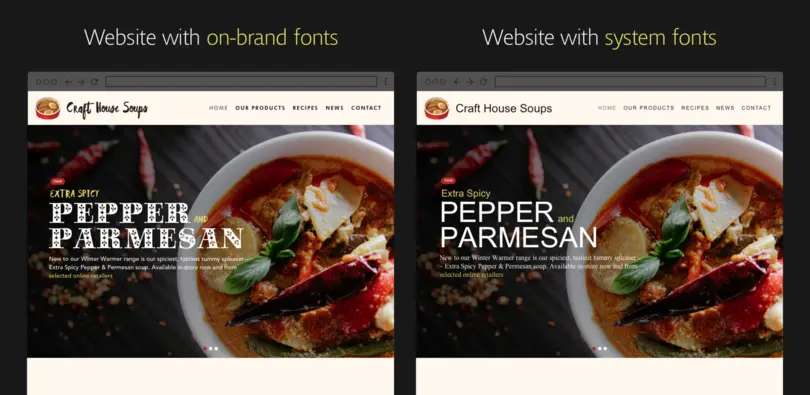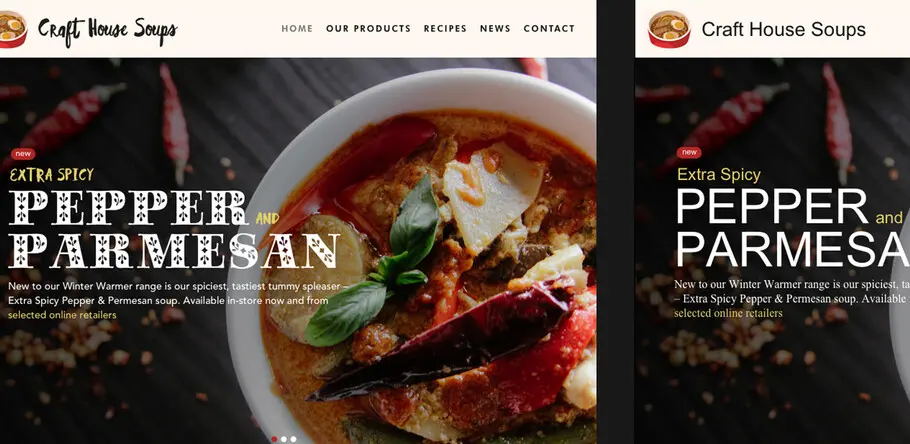
良い結果をもたらさないフォント:必ずしも期待通りの結果を得られない理由
「 Sharing your brand font with third parties—a design or marketing agency, a freelancer, or a vendor such as a printmaker—can be a tricky process. 」
Fonts behaving badly: Why you don’t always get the result you expect.
製品に合うフォントを選ぶ時、どれを選んでも問題なく思った通りの機能をすると思っていませんか?どこでどう使おうと、フォントはどこまで行ってもただのフォントであり、それ以上でもそれ以下でもない、と。 しかし実際はそうではありません。その場その場で考えなしにフォントを選んでしまうことによって、製品のビジュアルを大きく損ねてしまうことになりかねないのです。
フォントはさまざまな用途に合わせて作られた「ソフトウェア」と見ることが出来ます。例えば、システムフォントとも呼ばれるデスクトップフォントはコンピューターに既にインストールされた状態で届きますし、そういったフォントは印刷のプロジェクトで使用され、一部はウェブサイトでも使用されます。
その一方で、ウェブフォントは必要な時にサーバーとウェブサイトやデジタル広告からダウンロードされます。ウェブフォントは変化が早いデザインや、モバイルブラウジングに特に向いています。
フォントがブランドに与える影響
今後ブランドや会社にとって重要な事の内1つに、「ユーザーの全てのタッチポイントにおいて一貫性を実現させること」があります。
中でも、特に若いデジタルネイティブ世代は、無数に存在するプラットフォームのうち、自分の選んだもので円滑に製品やアプリなどを使用することが出来ることはもはや当たり前です。
Googleによると、オンライン上での利用を一つのデバイスである一つのアプリやウェブサイトを利用し始めたユーザーのうちなんと65%が、別のデバイスでも同じアプリやウェブサイトを使い続けています。
フォントを適材適所で活用できないと、ブランドとしての一貫性がなくなりかねません。これまで築き上げてきたブランドイメージが、ネット上では全く異なるものになってしまうこともあるのです。
そんなことが起きてしまえば社内はもちろん、ユーザーのブランドへの信頼も失いかねません。では、どのような時にこのような事態が引き起こされてしまうのか見てみましょう。
失敗事例1:デフォルトのシステムフォントの罠
システムフォントとは、OSに最初から組み込まれているフォントのことです。実はMac OS、Windows、どちらもバージョンの違いによって異なるシステムフォントを持っています。
例えばもし、お客様のOSに搭載されていないシステムフォントをウェブ上で使用してしまった場合、どうなるのでしょうか。
左側のウェブサイトはウェブフォントを使用して設計されており、あらゆるユースケースで一貫したブランド体験が保証されます。右側はシステムフォントで作成されており、デフォルトではランダムオプションが設定されています。
左のウェブサイトはどんな状況の場合でも一貫性を感じられるようなデザインになっています。逆に、右のウェブサイトでは、デフォルト設定のフォントに置き換えられてしまいます。
フォントをデフォルトに設定できる場合とできない場合があります。それによって、ユーザーは貴社が本来見せたいデザインを見ることができず、最悪ブランドのイメージが悪くなってしまいます。
その上、スマートフォンなどの携帯するデジタルデバイスはシステムフォントの数が少ないことが多くあります。
余談ですが、すべてがデジタルに変わりつつある今の時代、既に65%の人が携帯を使っていると言われています。ComScoreによると、「これからも増え続け、多くのユーザーが製作者の意図していない、残念な体験をすることになる」ようです。
失敗事例2:見づらいデジタル広告
近年米国では、デジタル広告用にフォントもオンライン配信を行うようになりました。デジタル広告用に認可されると、ウェブフォントは簡潔でわかりやすく、ブランドらしい形で配信されます。
ウェブサイトの主役はフォントです。ウェブフォントを活用することにより、よりダイナミックなコンテンツを作ることができ、さらに自分の思い通りにサイトをカスタマイズすることが可能です。
ウェブフォントは広告の質を文字面から保証し、どんなデバイスからであっても同じように表示されます。 代替案としては、テキストを画像出力してJPEG, PNGやGIFファイルの形でほかの画像と一緒に埋め込む方法が存在します。
ですが、このようにテキストを画像出力したものは特に解像度が高い画面上では見えにくく、別のスクリーンに合わせてカスタマイズしたり、リサイズしたりすることができません。
左側の広告では、ウェブフォントでテキストが明確かつ鮮明に表示されています。右側のテキストはイメージに埋め込まれており、結果的にオリジナルの外観が損なわれています。
失敗事例3:ブランドイメージに合わないHTMLメール
HTML形式のEメールは、私達がブラウザなどで閲覧しているウェブサイトのように裏で動いているコードと画像とテキストの組み合わせで成り立っています。裏でHTMLコードが動いているので、こういったHTML形式のEメールでもウェブフォントは活躍します。
Eメールでも、フォントを指定していなければ、テキストは通常、一般的なシステムフォントなどで置き換えられています。画像の中にデザインの一つとして組み込まれていることもあります。Eメールのメッセージでもウェブフォントを使用することで、企業のブランドイメージをメールでも保ったまま送付することが可能です。
もちろん全てのEメールクライアントがウェブフォントの使用に賛同しているわけではないのですが、Appleの提供しているメールアプリケーションやAndroidで提供されているアプリケーション多くは賛同しており、実際にこれらのアプリケーションでメールを確認するとHTMLコードが正しく読み込まれ、ウェブフォントも活用することが可能です。
ちなみにウェブフォントがサポートされていない場合にも、代替フォントを指定することができるようになっています。 ウェブサイトと同様、HTML形式のEメールでも同じフォントを使用することで一貫したブランドの体裁と企業のブランドの雰囲気を保証できるようになるのです。
ウェブサイトと同様に、HTMLメールでブランドイメージに合ったウェブフォントを使用することで、ブランドイメージに合った一貫したルック&フィールが保証されます。
モバイルの成長とともに、ウェブフォントはEメールでより一般的に使用されるようになるだろうと言われています。 今、ウェブフォントを組み入れることで、より良い体験をユーザーに届けることができます。
失敗事例4:社を超えたフォントの共有範囲で悩む
製品開発などをデザイン会社やマーケティング会社、フリーランス、印刷会社等のベンダーなどの第三者と行う場合、フォントによっては共有しにくい場合があります。
例えば、フォントを複数台のコンピューターにインストールできるようなライセンスを取っておかなければ、複数社にまたがってフォントを共有することはできません。 企業ごとにフォントを購入しなければならず、コストが上がってしまうため開発が滞ってしまう場合があります。
結果、ノーブランドのフォントを選ぶか、フォントを違法で利用することになってしまいます。
フォントの購入の際に考えるのがどのライセンスを購入するかですが、これにはまず、フォントを使用する場面を見極めて、どのようなフォントが必要か判断する必要があります。 ウェブサイトとデジタル広告が受け取るインプレッション数を集計し、どの程度のライセンスのウェブフォントを購入すべきなのか、スマートフォンのアプリケーションに組み込むかどうかなどの将来的な話も見据えて考えます。